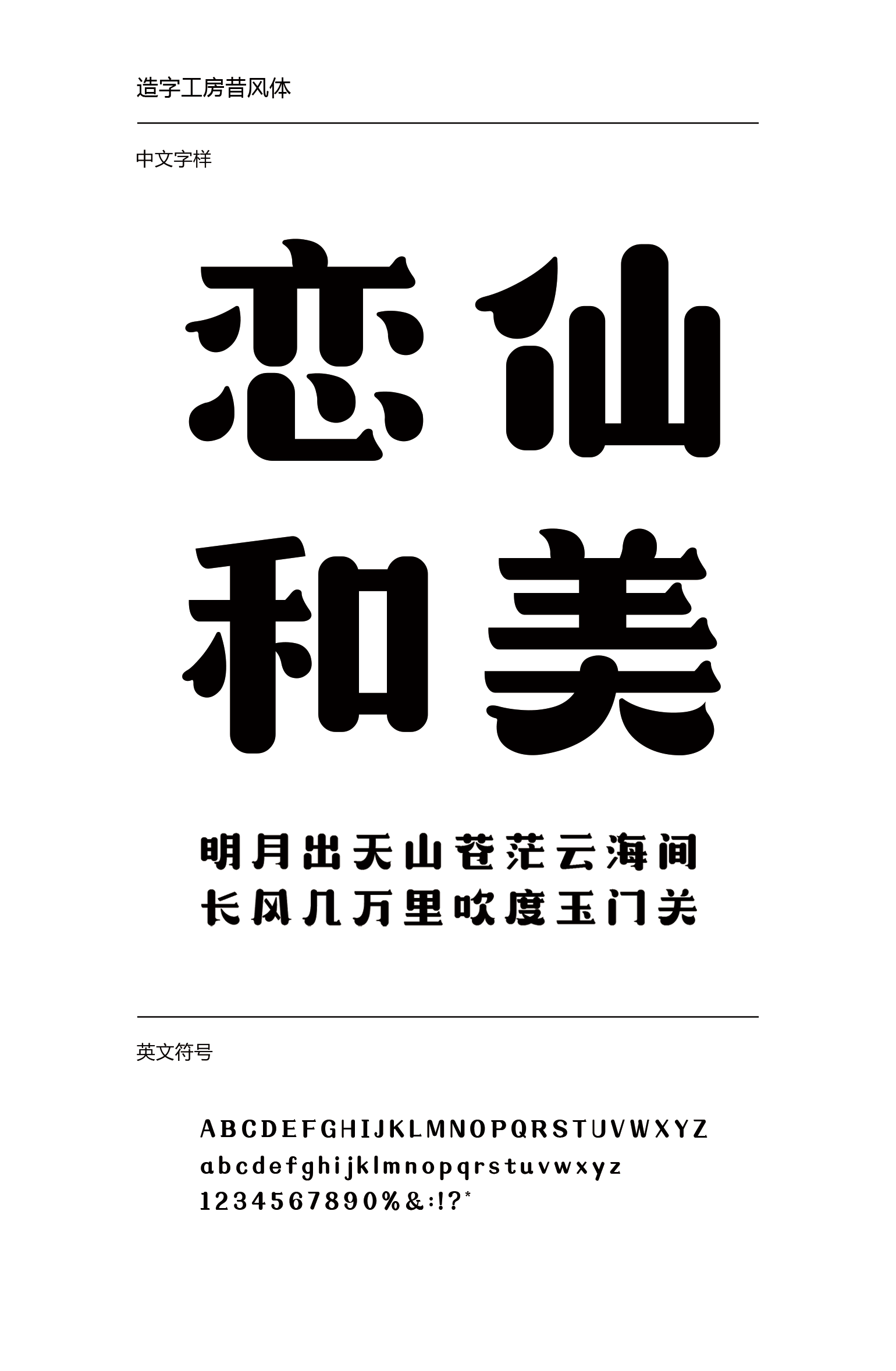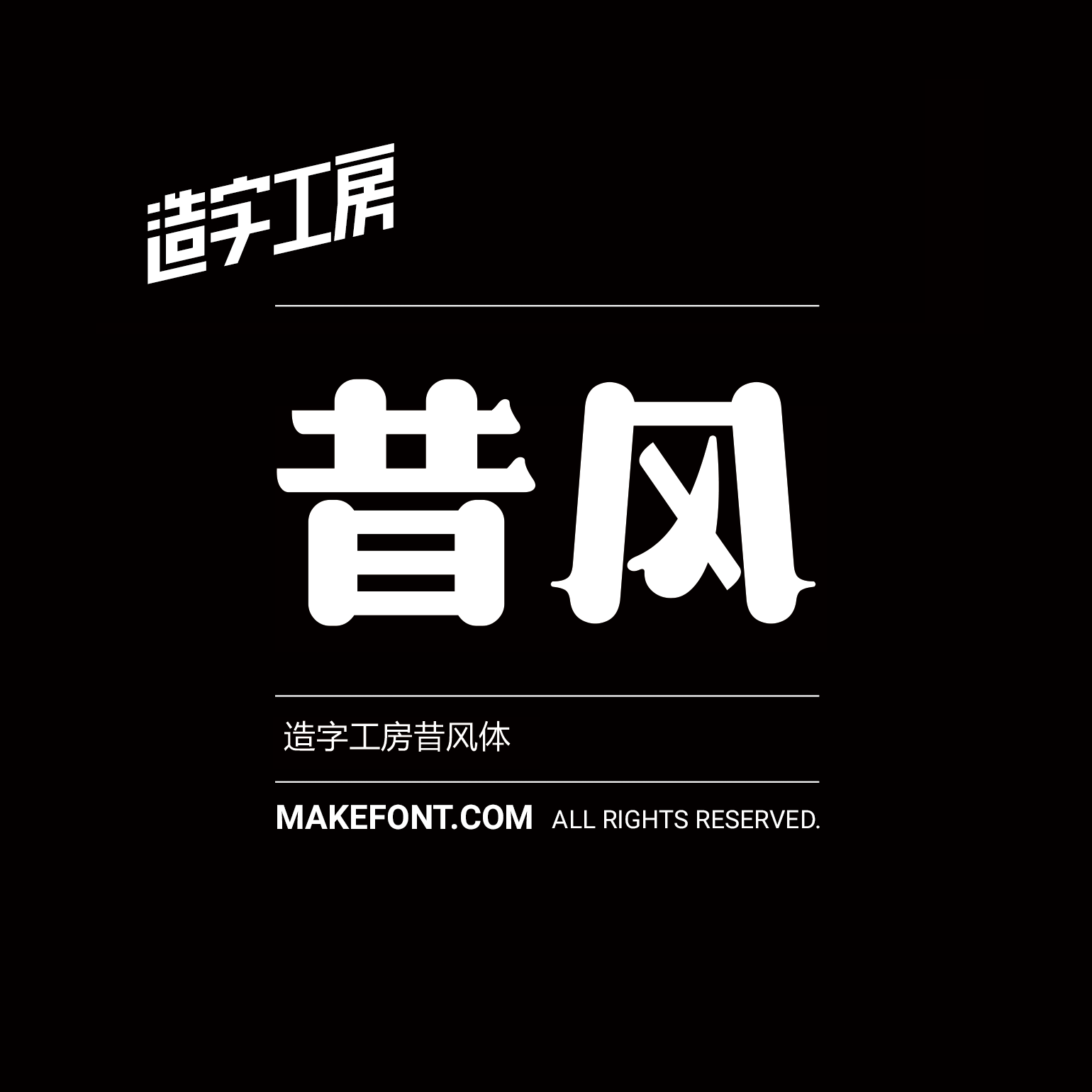
造字工房昔风体 造字工房昔风体设计说明 造字工房昔风体风格遒劲润雅,结构随性自由,笔势恍如飞鸿戏海,结体严紧,笔画穿插紧密、粗劲圆润、浑厚宽博,令其笔力恬润、婉畅又不失端正。适用于大标题及个性品牌设计推广等环境。本字体为简体字库,采用OpenType/CID格式,Adobe-GB1-5编码。基于中华人民共和国GB2312-80字符集标准,另按需添加101个汉字。共收容字数6864CJK汉字,ASCII常用字符100个。 造字工房昔风体下载地址 点击下载